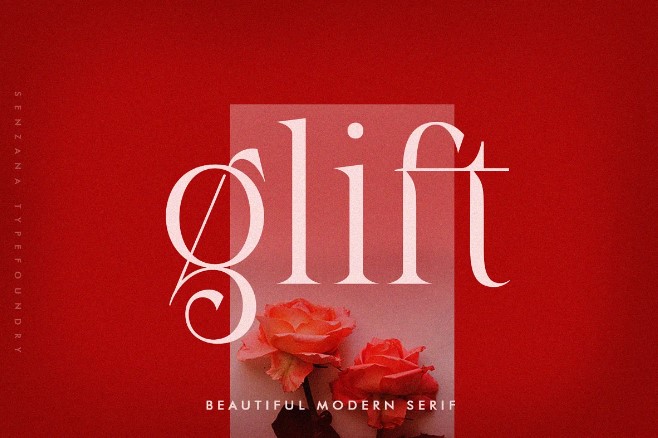
Creativemarket Glift Font
[Creativemarket] Glift Font
По этому случаю я хотел бы представить новый шрифт, который называется "glift"
Этот шрифт имеет современный, винтажный и красивый стиль.